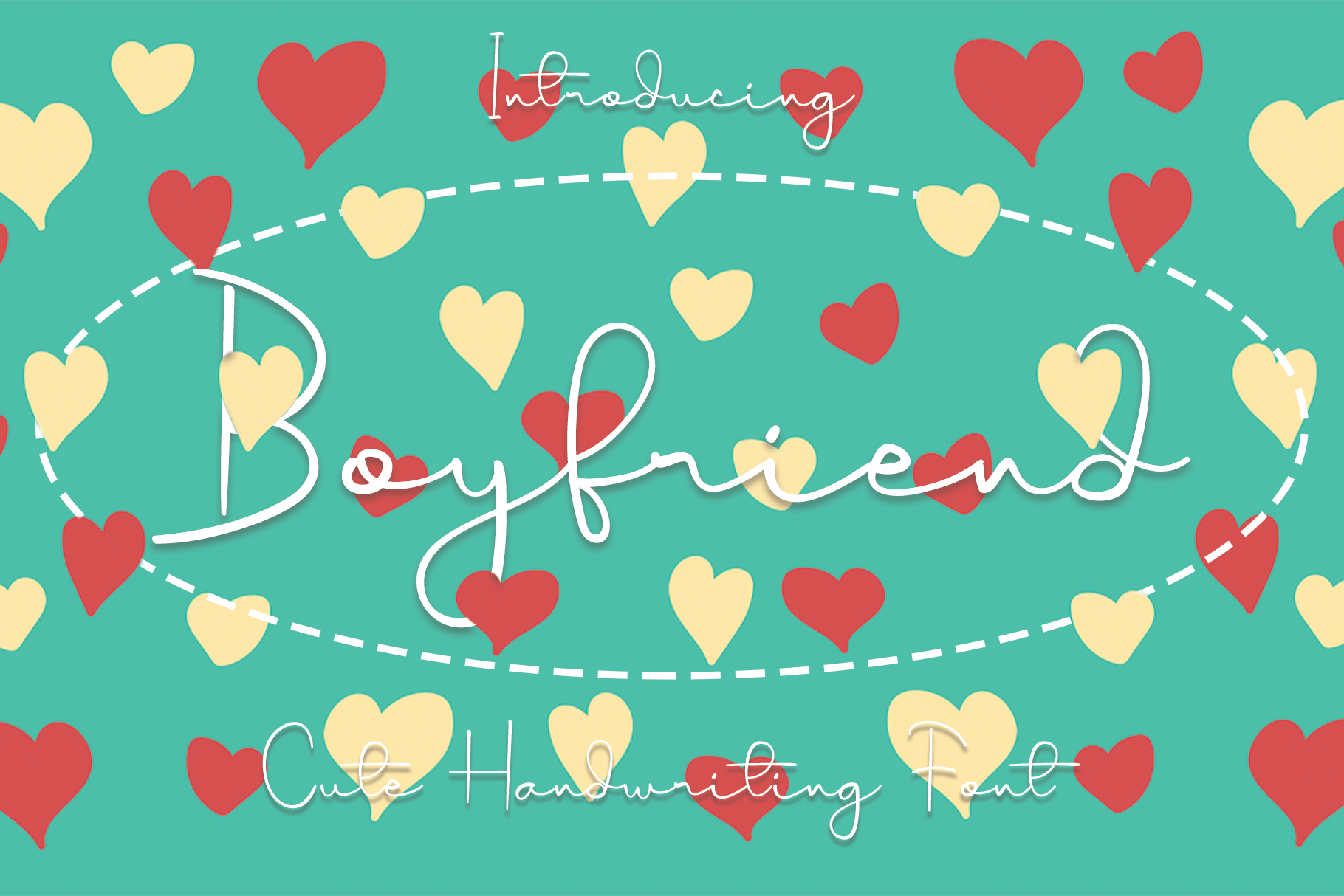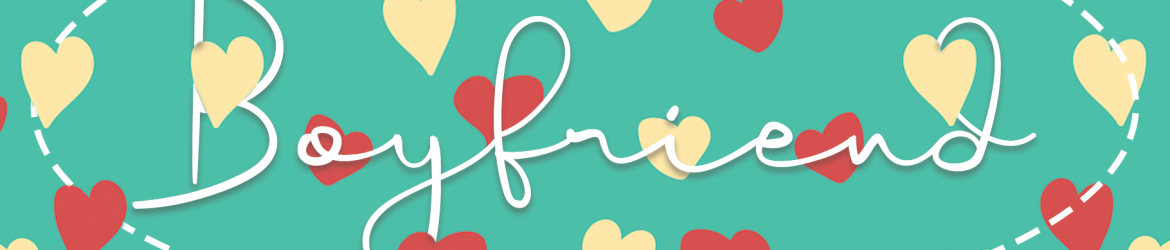
Boyfriend Handwritten Font – Download Grátis
Esta é uma tipografia script elegante e refinada que transmite sofisticação e elegância. Suas alternativas estilizadas e ligaturas fazem dela uma escolha perfeita para qualquer projeto, seja ele para anúncios de moda, cartões personalizados ou até mesmo como parte do design de interiores. Ela possui um charme único que a torna não apenas versátil, mas também capaz de enriquecer qualquer obra de arte ao qual é adicionada. Seja você um designer de roupas ou alguém com uma paixão por criar designs digitais, esta fonte ‘Boyfriend Handwritten’ criará um visual sofisticado e único para seus projetos.